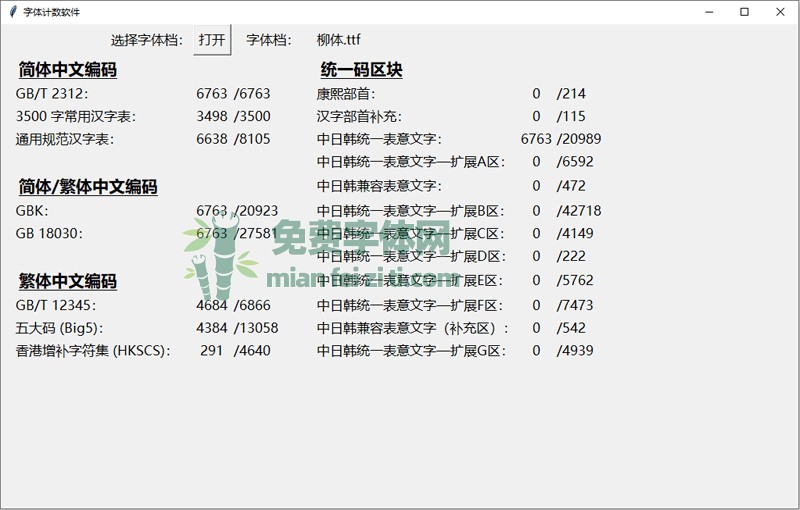
字体名称: 柳体
柳体是2006年的一款GB2312字体,这款字体虽然命名柳体,但跟我们印象的柳体很不一样。这款字体虽然字符数比较少,但字形很有特点,有点刻字的味道。并且打印出来后的阅读效果不错,在生僻字不多的书面材料(例如领导讲话稿)里用应该很合适。按照原作者的说法,这是一款用算法模拟生成的字体。点阵来源为GPL字体 intlfonts-1.2.1,使用了其中的24pix GB2312字型。